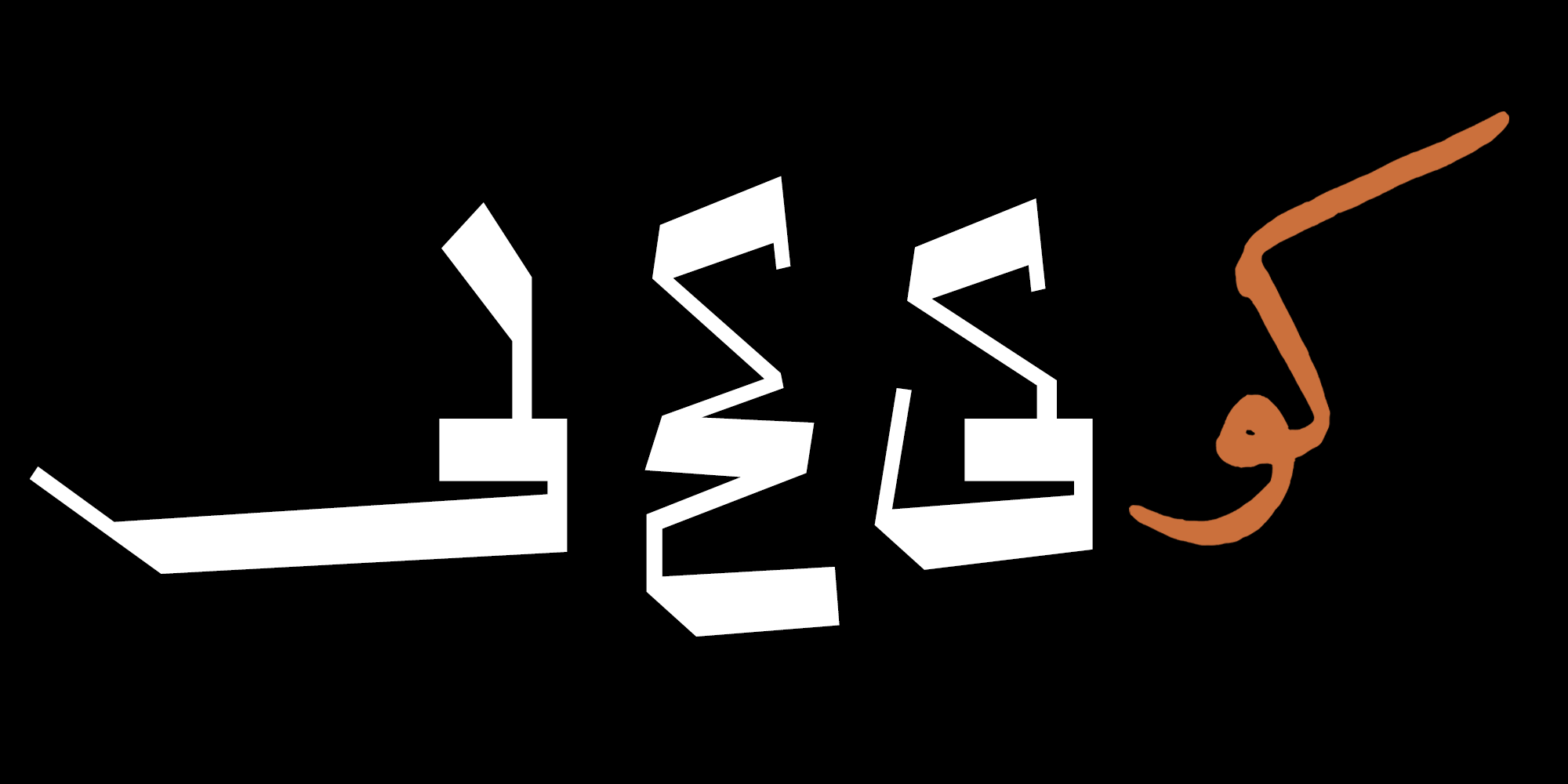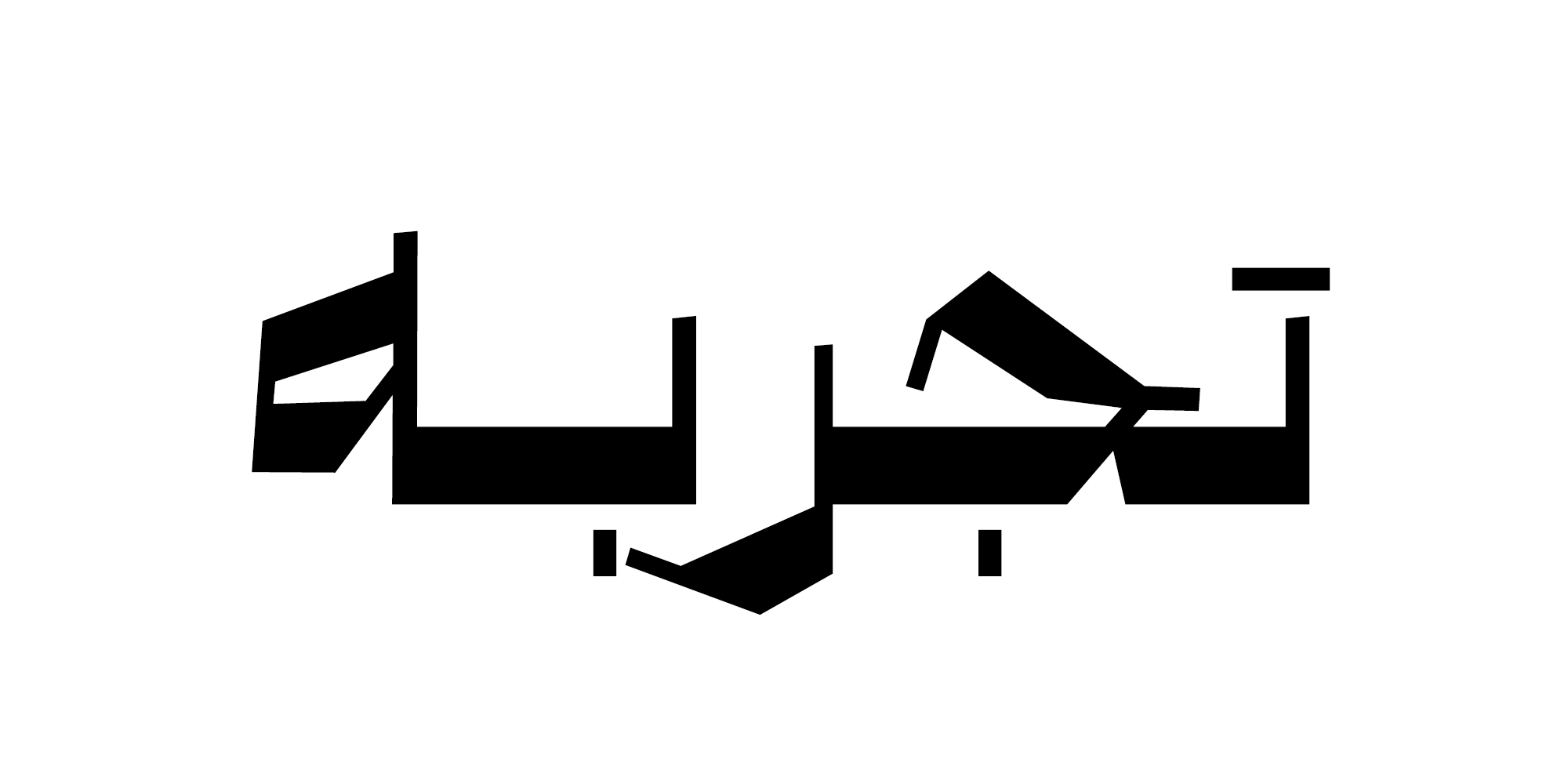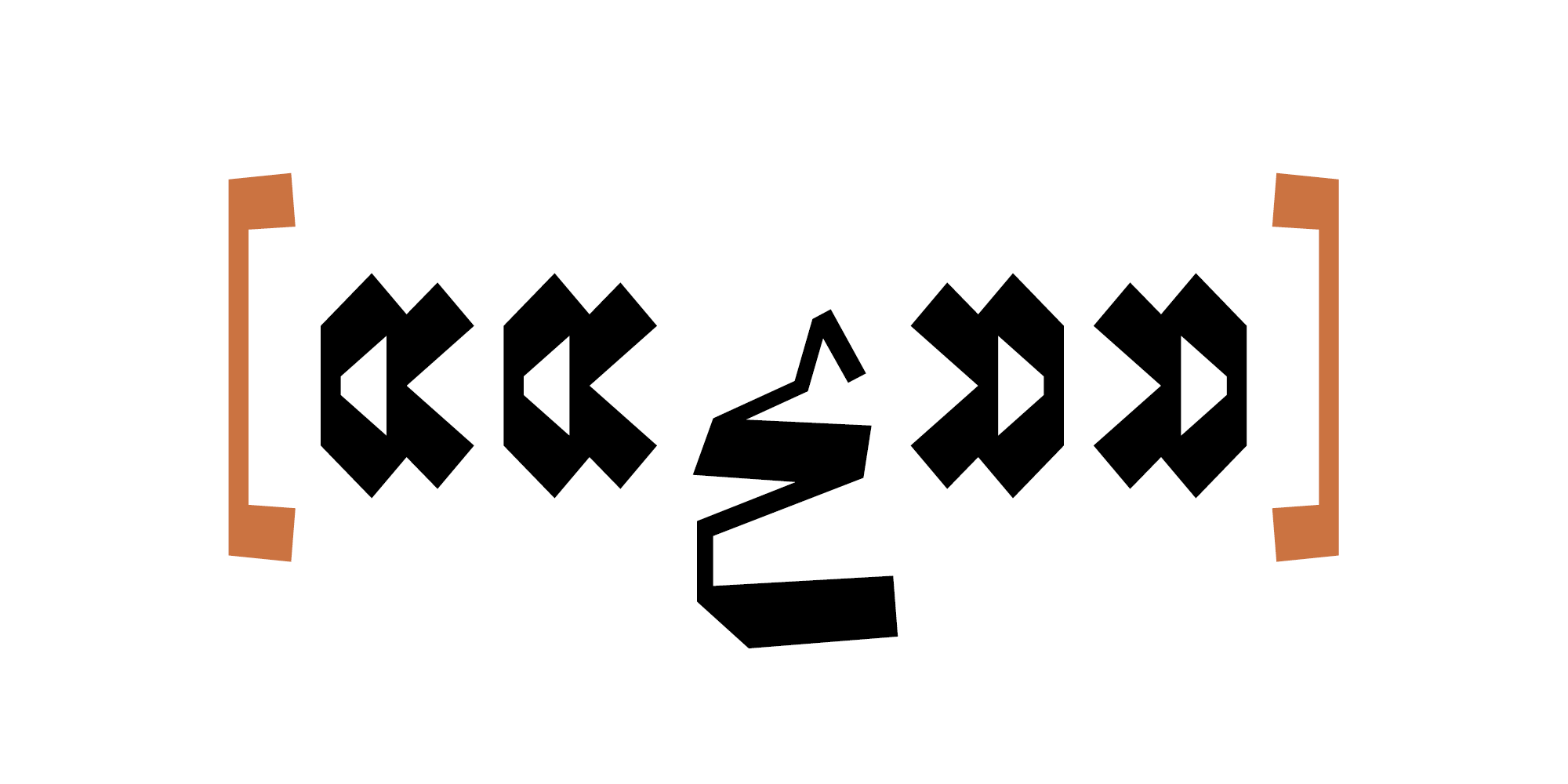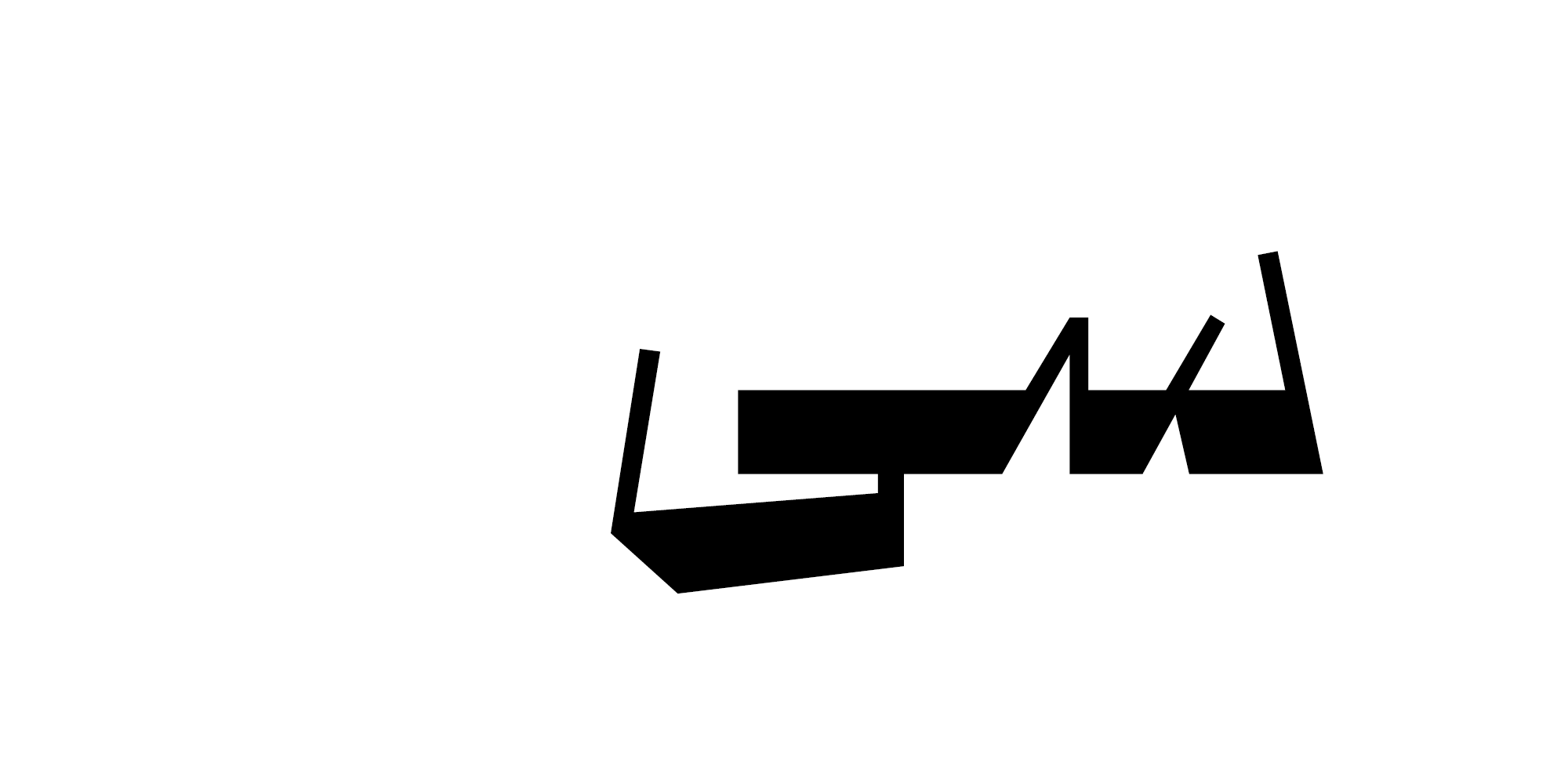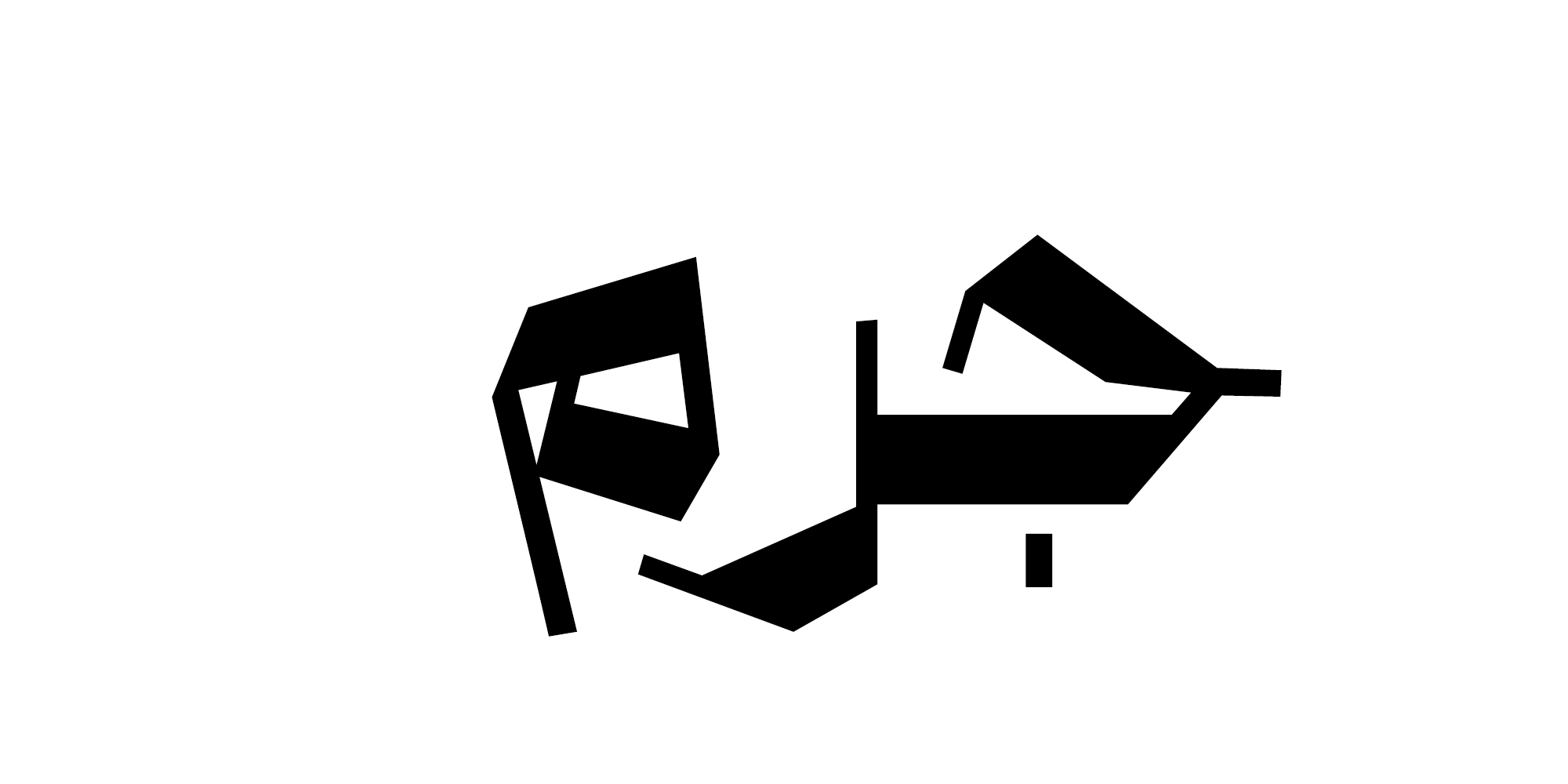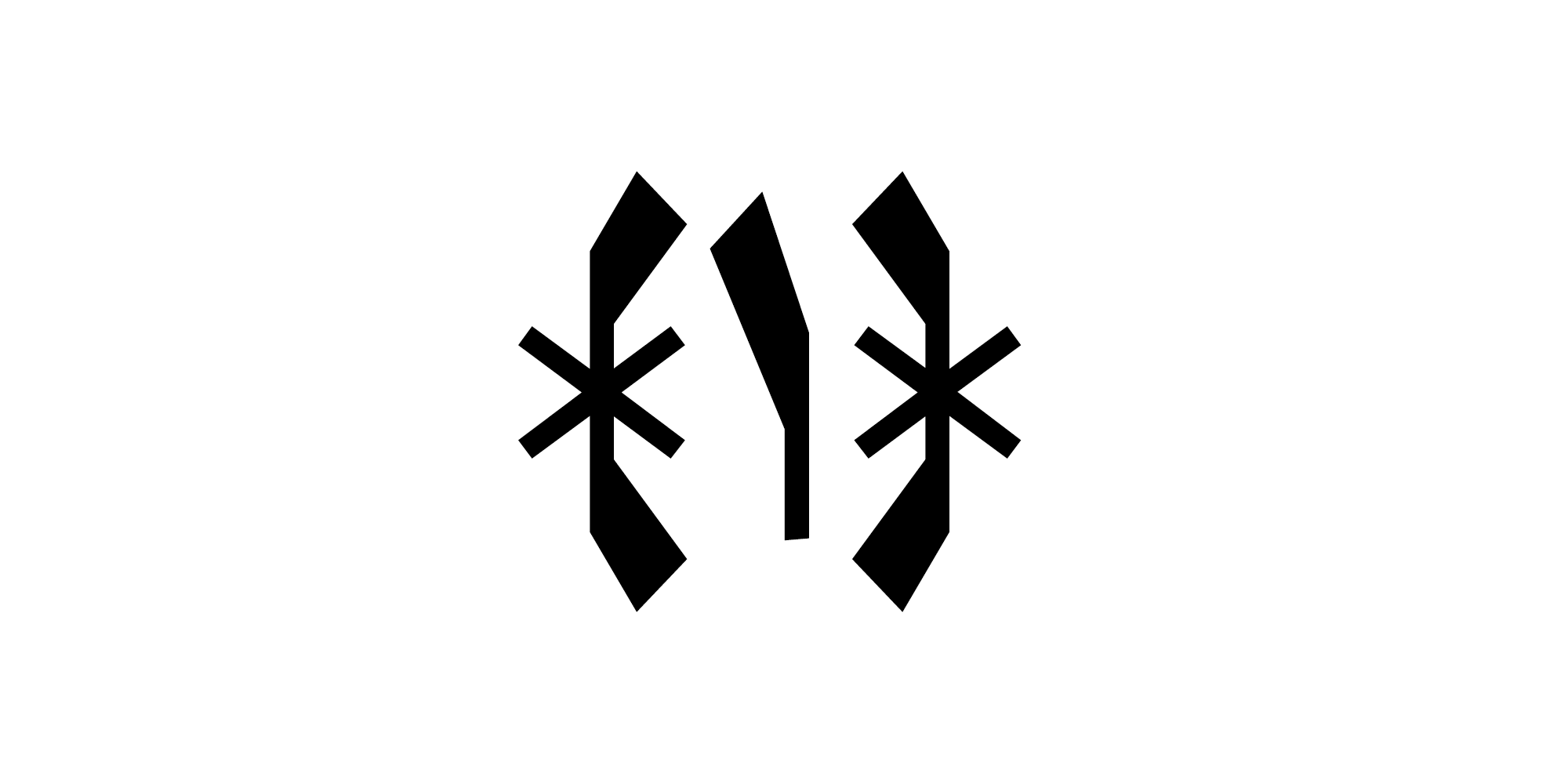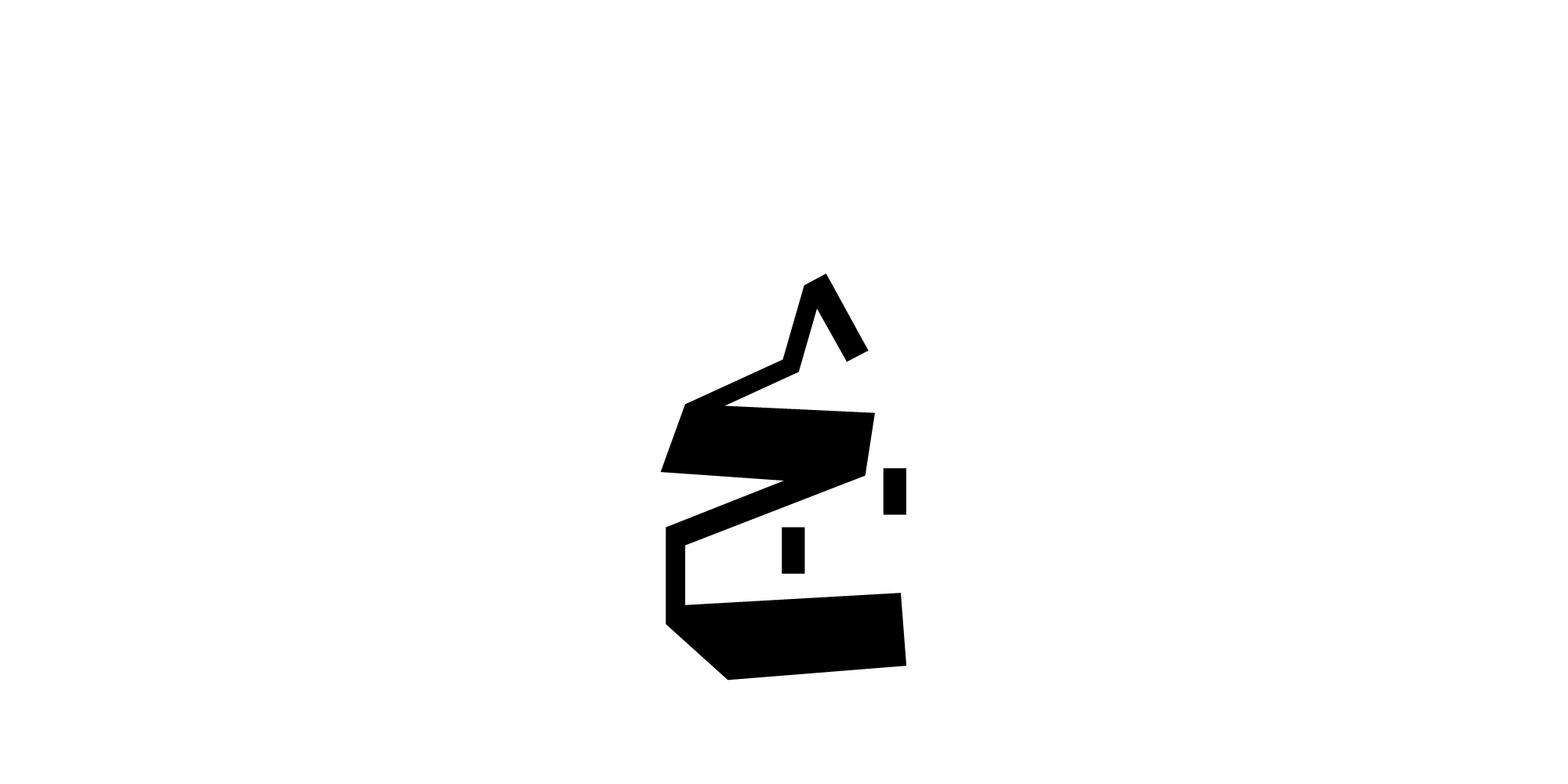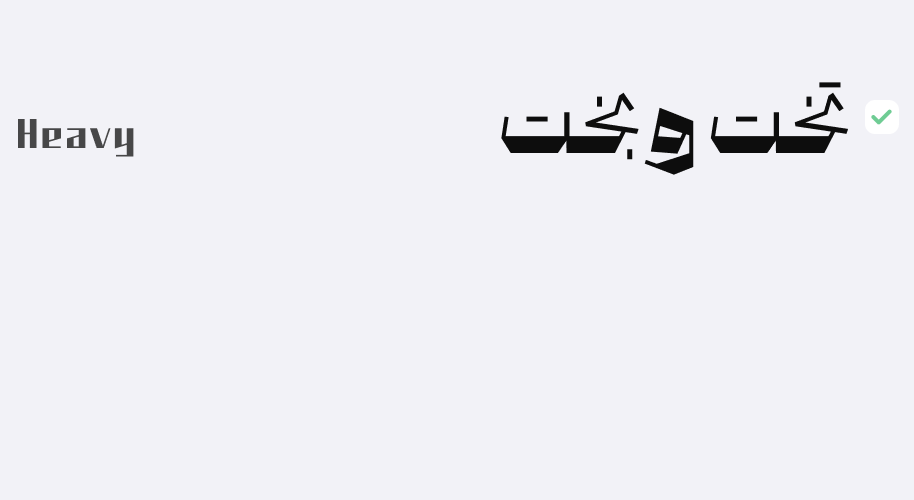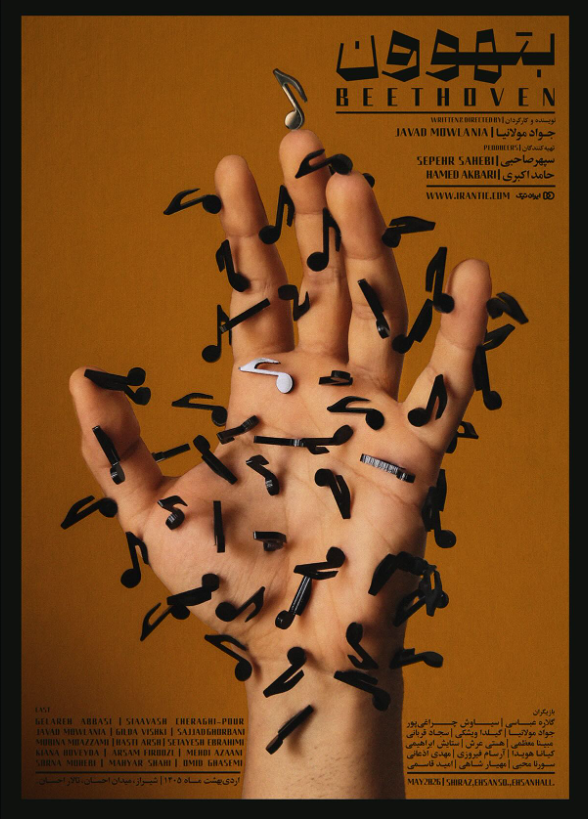
خط نسخ احمد نیریزی
در تمام مدت طراحی «نوشت» کتاب «رسم المشق خط نسخ ایرانی» تالیف استاد گرانقدر محسن عبادی به عنوان تنها منبع الهام فرمی در کنارم بود.
هندسه
دوست هنرمندی در جایی گفته بود « فرم هندسی، بر خلاف نامش، میتواند حاوی نوعی جادو و جنون باشد.» پیش از طراحی «نوشت» هرگز گمان نمیکردم میتوان تایپی هندسی و آن هم بر پایه یک خط سنتی طراحی کرد.
با فعال کردن discretionary Ligatures در تنظیمات Open Type ترکیبات جایگزین منتهی به « ج چ ح خ»، «ر»، «هـ» و «ی» در دسترس خواهد بود.
با فعال کردن Stylistic Alternates در تنظیمات Open Type امکان کنترل بعضی از کشیدگیها و تغییر شکل «ر ز ژ» در دسترس خواهد بود.
همچنین با فعال کردن Stylistic Set در تنظیمات Open Type حروف جایگزین «م» و «ی» و با فعالسازی Swash حروف کشیده «س ص ق ک ن م ی» در دسترس خواهد بود.
«نوشت» از زبانهای فارسی ، عربی، کردی، اردو و انگلیسی پشتیبانی میکند.